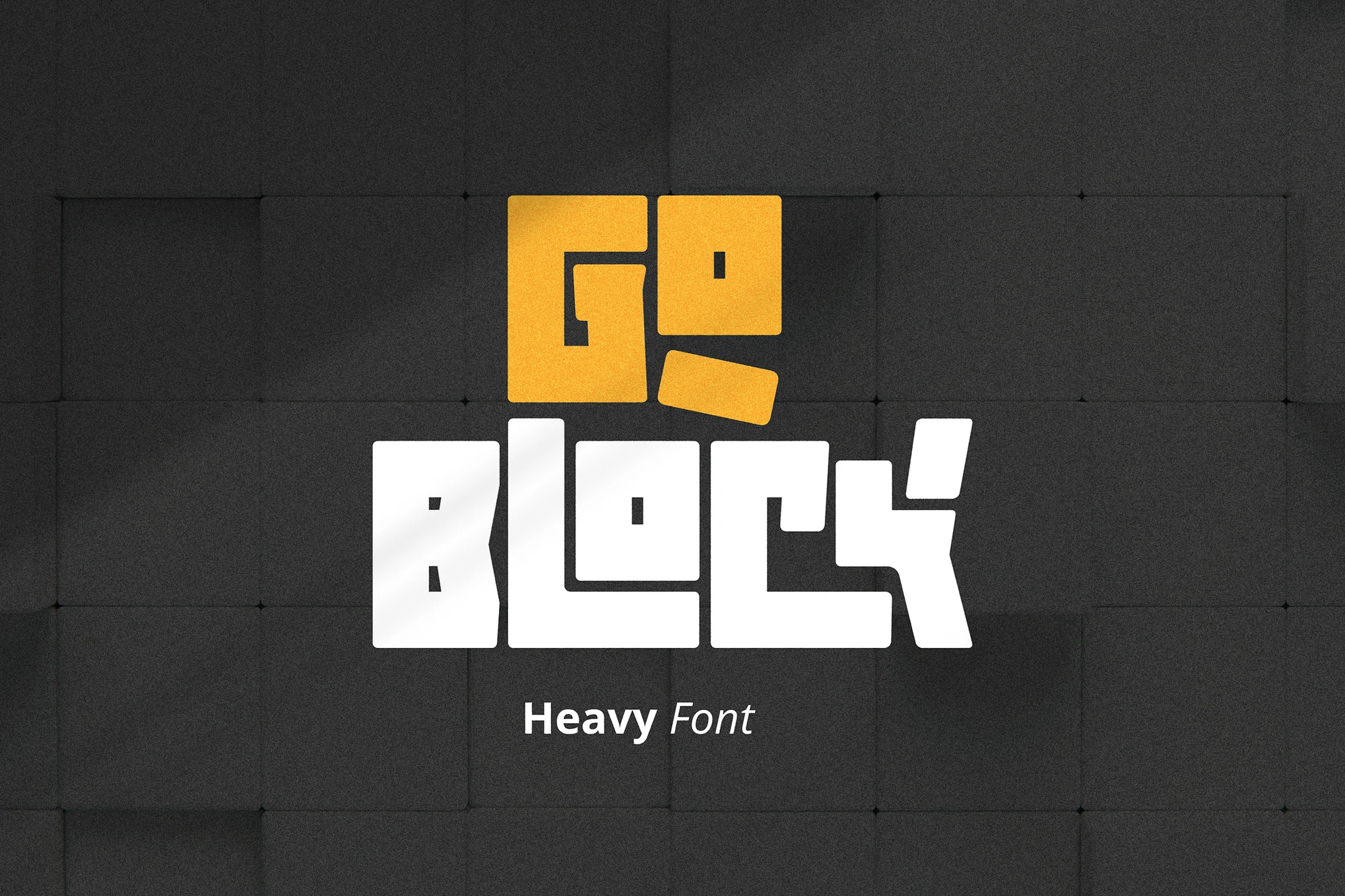
دانلود فونت Goblock – Heavy Font
معرفی فونت Goblock – یک تایپفیس قدرتمند و برجسته که برای برندهایی طراحی شده که میخواهند جلوهای جسور، قوی و ماندگار داشته باشند. این فونت با ضخامت بالا و طراحی فوقالعاده سنگین خود، فوراً توجه را جلب کرده و هویتی مقتدر و محکم به برند شما میبخشد.
⭐ ویژگیها:
- حروف پایه لاتین
- حروف بزرگ و کوچک
- آلترناتیوها (Alternates) و لیگچرهای متنوع
- اعداد و علائم نگارشی
- نمادهای ارزی (Currencies)
- پشتیبانی چندزبانه (Multilingual Support)
📌 اگر به دنبال یک فونت برای طراحی لوگو، هویت برند، بستهبندی محصولات یا حتی عنوانهای گرافیکی قدرتمند هستی، Goblock گزینهای عالی و جسورانه است.